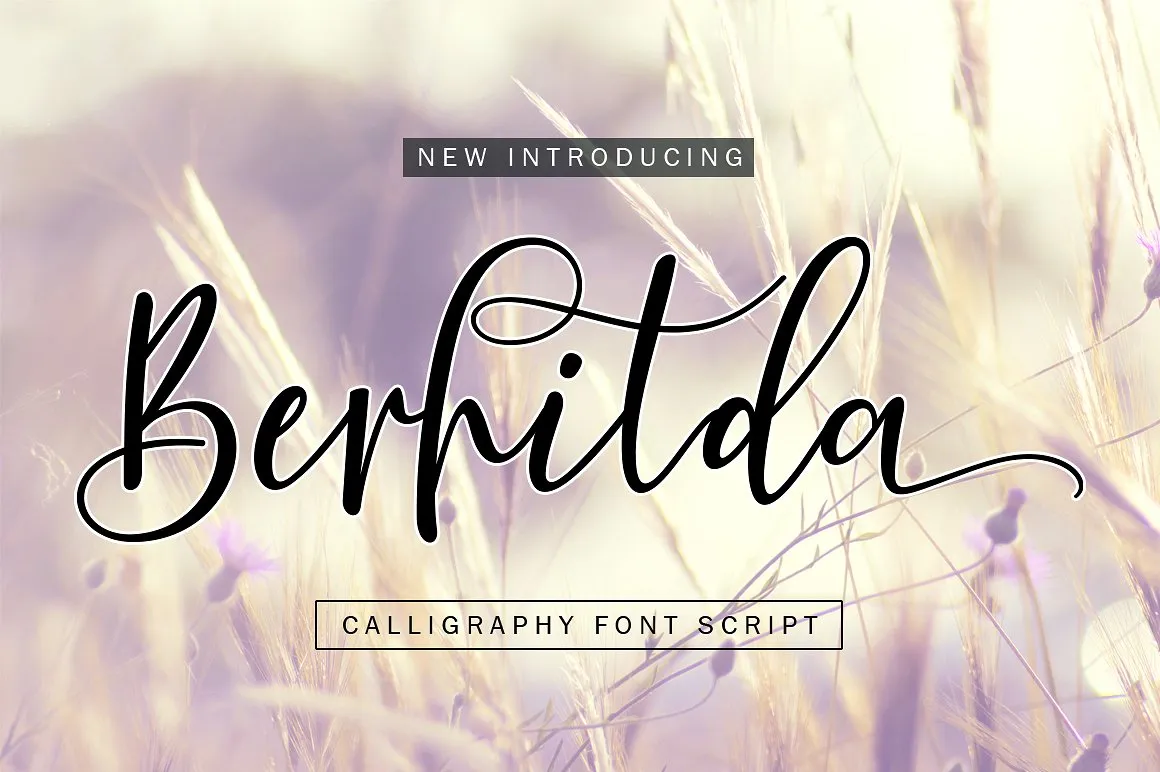
Berhilda Script Font
A ‘Berhilda Script’ é uma nova tipografia handmade que oferece frescura e originalidade para os criadores de design. Esta fonte perfeita se destaca no ambiente do branding, convites para casamentos, revistas, talheres, cartões de visita, frases, panfletos e muito mais. A característica única desta fonte é sua capacidade de oferecer 343 gráficos, permitindo escolha direta dos caracteres conforme seu gosto. Com muitas variações e opções para cada letra, a ‘Berhilda Script’ lhe dá a liberdade de personalizar suas escolhas de design, tornando-a uma ótima adição para estilos gráficos criativos. Se você deseja experimentá-la antes de comprá-la, não hesite em dar este fonte um chance.